네덜란드 디자인 기행_강문식 디자이너
앞으로 폰트클럽을 통해 네덜란드에서 일어나는 다양한 예술, 문화 뉴스를 전달하고자 한다. 그래픽디자인을 중심으로 하되 영역을 한정하지 않고 그래픽 디자인을 아우르는 다방면의 문화 예술로 확장된 시각 뉴스를 구성할 예정이다. 먼저, 강문식 디자이너를 소개한다. 강문식 디자이너는 계원예술대학교와 네덜란드 암스테르담의 헤릿 리트벨트 아카데미(Gerrit Rietveld Academie)에서 공부했다. 2012년에는 <브르노 비엔날레(Brno Biennial)>에 참여한 바 있고, 올해 <타이포잔치 2013>에 참여해 새로운 작업을 선보이기도 했다. 그를 만나 디자인 작업에 대한 이야기를 나눴다.
<How to make your life hard in one day>, 2011
오경민: 리트벨트 졸업 작품이자, 문식씨가 직접 운영하는 +082Press에서 출판된 <Unsigned Signs>부터 시작하죠. 다른 문화, 다른 세대, 다른 언어에서 오는 소통의 어려움을 감수하면서 두 사람이 가진 공통 관심사, 글자(Letter)에 대한 대화를 나눈다는 내용이 인상적이었어요. 암스테르담의 첫인상으로 책의 소개 글을 시작했는데요, 저와 비슷한 환경에서 참 다른 생각을 했다고 느꼈어요. 저는 디자이너의 손이 전혀 닿지 않은 것만 같은 암스테르담 거리의 간판들을 보며, 소문으로 듣던 훌륭한 더치 디자인(Dutch Design)들은 어디에 숨어 있는가 하는 의문이 들었거든요. 문식씨는 저와는 다른 것에 주목했네요.
강문식: 말씀하신 대로 매체에서 봐 왔던 더치 디자인을 생활 속에서 보기는 힘들었어요. 오히려 자전거를 타고 매일 지나가는 운하의 다리에 새겨진 글자들이라던가 오래된 카페에 페인팅 된 레터링들이 제 삶과 더 밀접하게 연결되어 있었죠.
오경민: <Unsigned Signs>에 대해 간단히 설명해 주실 수 있나요?
강문식: 암스테르담의 거의 모든 간판 레터링 작업을 하신 할아버지, 레오 부커봄(Leo Beukeboom)에 관한 이야기에요. 단순히 레오와 그의 작업을 소개하고자 했다기보다는, 레오를 통해서 제 얘기를 하고 싶었어요. 레오와 제가 어눌한 외국어(영어)를 보완하기 위해 손동작이나 그림, 그리고 불완전한 손글씨 등을 이용해서 어렵게 소통하는 그 상황이, 마치 네덜란드어를 읽지 못하기 때문에 패키지의 모양과 디자인을 이용하여 샴푸와 음료수를 구분하는 방식으로 네덜란드에서 생존하고 있는 저의 상황과 유사하다는 생각이 들었거든요. 그런 미스커뮤니케이션(miscommunication)을 책에 담고 싶었어요. 당시 서양인의 시각으로 일본을 바라본 롤랑 바르트(Roland Gerard Barthes)의 <기호의 제국 (Empire of Signs)>을 읽으면서, 동양인의 시각으로 서구를 바라보는 반대의 상황을 만들어 보고 싶었던 것 같아요.
책 구성은, 그의 레터링 작업 아카이브(archive) 뿐 아니라 오점투성이의 인터뷰, 그리고 레오와 저의 협동 작업, 이렇게 세 가지 부분으로 되어 있어요. 협동 작업은, 레오가 사고로 오른손을 다치면서 미완성 상태로 남아 있는 마지막 레터링 작업을, 제가 직접 레오의 도구들을 이용해서 완성해 보는 것이었죠. 이 부분에서조차도 미스커뮤니케이션에 의한 실수가 있었어요. 그려야 할 글자들을 레오 할아버지가 왼손으로 구불구불하게 적어 주셨는데, 제가 그것을 잘못 읽는 바람에 최종 작업에 그 오자가 그대로 반영되었어요. 하지만 이런 실수도 프로젝트 일부분이라고 생각하고 수정하지 않았어요. 각 세 부분은 차례대로 연결되어 있다기보다는, 서로 다른 층들이 한 책 안에 공존하는 구조를 하고 있어요. 페이지 구성에서도 미스커뮤니케이션을 반영하고 싶었거든요.
오경민: 레오는 어떻게 만나게 되었나요?
강문식: 유지원 선생님 소개를 받았어요. ISTD TypoGraphic 67호 <I wonder> issue 에서 레오를 발견하시고, 레터링에 관심이 있는 저에게 정보를 주셨어요. 직접 만나보고 싶지만, 암스테르담에 갈 수가 없으니 현지에 있는 제가 직접 만나보길 권유하셨죠.
오경민: 올해 봄 암스테르담의 독일문화원에서 진행된 <암스테르담 독일문화원의 평양 ? 열람실 재개원> 전시에서, 사라 반 더 하이데(Sara van der Heide) 프로젝트를 위해 만들었던 레터링 작업도 <Unsigned Signs>가 연결고리가 된 건가요?
강문식: 네. 작년 여름 브라질 리우데자네이루(Rio de Janeiro, Brazil)에서, 리트벨트 아카데미 졸업반 학생들과 선생님들이 함께 기획한 워크숍이 열렸어요. 1주일간 임시 학교를 여는 컨셉의 워크숍이었고, 각 학생이 자신의 워크숍을 직접 기획하고 운영했죠. 저는 물론 레터링에 관한 워크숍을 진행했고요. 리트벨트 아카데미 선생님인 사라가 그 워크숍을 보셨고, 레터링이 필요한 본인의 프로젝트를 위해 기술적인 도움을 요청했어요. 독일문화원 전시에서는 레터링 작업 이외에도, 당시 전시에 들어가는 전체적인 디자인 작업을 다니엘 노레가드(Daniel Nørregaard)와의 협업으로 진행했어요.
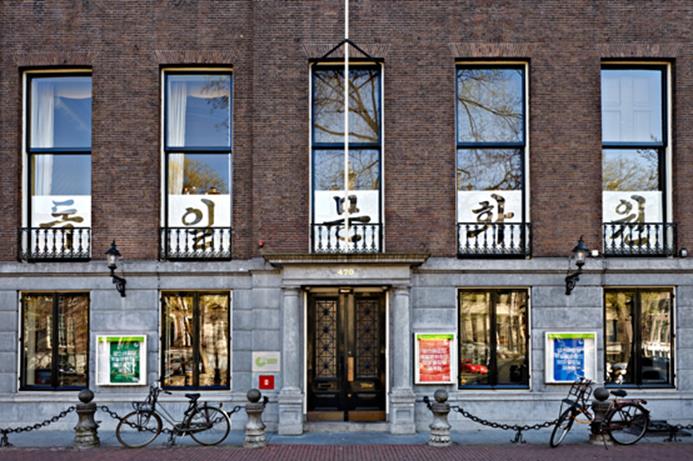
<암스테르담 독일문화원의 평양 – 열람실 재개원>, 2013 독일문화원 암스테르담 레터링
컨셉: 사라 반 더 하이데(Sara van der Heide)
레터링 페인팅: 강문식
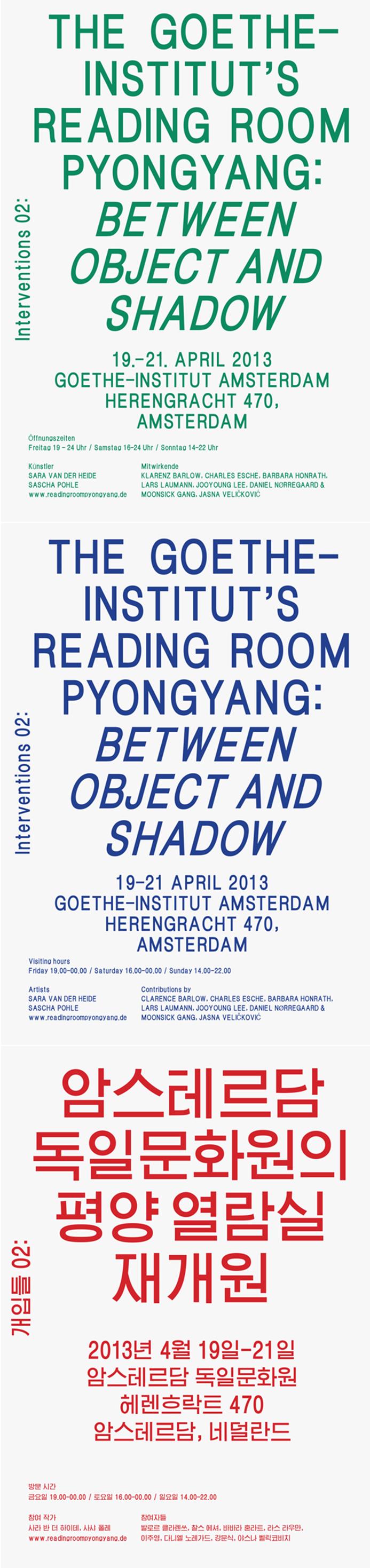
<암스테르담 독일문화원의 평양 – 열람실 재개원> 프린트 디자인, 2013
다니엘 노레가드(Daniel Nørregaard)와의 협업
오경민: 최근 디자인한 <공포영화 서바이벌 핸드북> 표지 디자인이 인상적이었어요. 한국의 디자이너들이 쉽게 쓸 생각을 하진 않을 것 같은 서체를 간결한 그래픽 어법과 조합하여 잘 풀어냈다고 생각해요. 사용한 글자 모양이 레오의 컬리 레터(curly letter)와 약간 비슷하다는 느낌을 받았는데, 레터링에 관한 관심이 연결됐다고 볼 수 있나요?
강문식: 그렇게 보일 수도 있겠지만, 접근은 약간 달랐어요. 기존에 많이 사용되는 서체들과는 차별화되는 서체를 찾고 싶었어요. 새로우면서도 책의 주제와 연결되는 모양새를 가진 서체들을 조사하다가 이 서체(물감체, 태시스템)를 발견하게 되었죠.
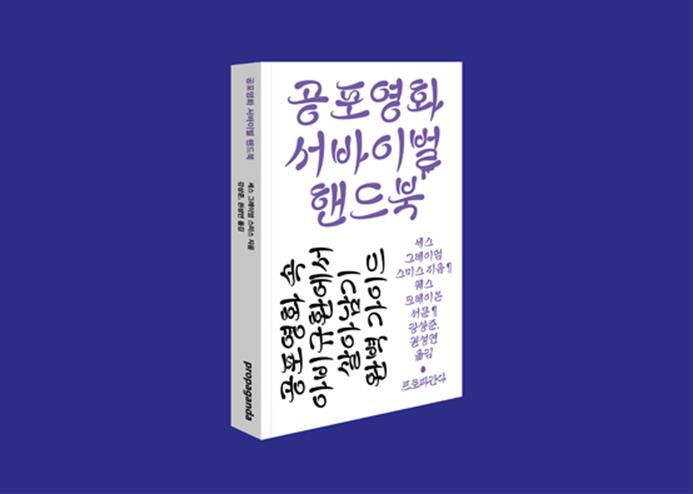
<공포영화 서바이벌 핸드북>, 프로파간다 출판, 2013
오경민: 작년 <브르노 비엔날레(Brno Biennial >에서 전시됐던 벨리고딕(Belly Gothic)도, 벨고딕(Bell Gothic)에 강문식씨 나름의 손맛을 가미한 것으로 보이던데요.
강문식: <공포영화 서바이벌 핸드북>은 서체 형태가 주는 느낌이 디자인의 중요한 부분이었다면, 벨리고딕은 시스템적인 문제를 건드린 것이었어요. 벨고딕이 가지고 있는 기술적 장점이자 특징인 잉크트랩이 인쇄기술의 발달로 그 의미가 퇴색되고 현재에는 스타일로만 남게 된 상황을 과장해서 표현한 서체였죠.
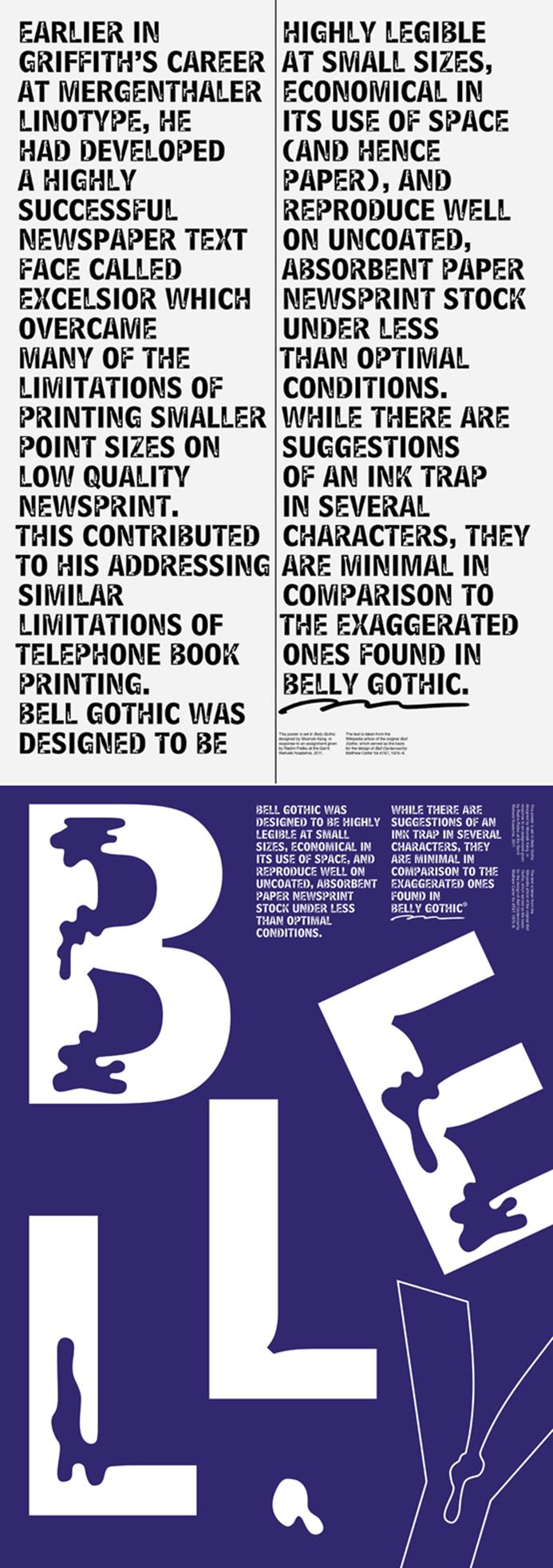
<Belly Gothic>, 2012
오경민: 각 프로젝트가 접근은 달랐지만, 비규범적, 비정형적 형태로 우연처럼 연결됐네요. 이번엔 학교 얘기를 해볼까요? 리트벨트 아카데미(Gerrit Rietveld Academie)에서의 생활은 어땠나요?
강문식: 한국 대학교와의 시스템적 차이가 가장 크게 다가왔어요. 교수, 조교, 학생 사이의 위계가 명확하게 구분된 조직이 아니라 각자의 역할을 따라 필요할 때 연결됐다가 해체되는 평등하고 자유로운 점 조직 같았어요. 그리고 모든 프로그램은 학생들이 공부하고 싶어하는 부분을 지원해 주기 위한 방향으로 디자인되어 있다는 느낌이었죠. 교육 내용에서도 지식 전달 위주가 아니라 주로 개념에 대해 접근했고, 필요한 지식은 학생들이 자율적으로 채워 넣어야 했어요. 지금은 당연한 것들이 돼버렸지만, 처음 학교생활을 시작할 당시에는 굉장히 새롭게 느껴졌어요.
오경민: 2011년 프라하에서 진행된 리트벨트 학생 전시회 <Rietveld at Prague>를 위해 디자인한 포스터에서, 리트벨트 아카데미와 리트벨트가 디자인한 의자를 단도직입적으로 연결한 부분뿐 아니라, 저명한 디자이너의 고급 의자를 대중적으로 친숙한 광고 전단 형식과 결합한 부분이 재미있었는데요, 문득 2년 전 강문식씨와 한 대화를 떠오르게 하더군요. “디자이너 친구와 익명으로 ‘찌라시’ 디자인 회사를 만들기로 했다”고 농담처럼 말했었죠. 이 포스터는 그 야심을 실현해 본 건가요?
<Rietvelt at Prague>, 2011
안근표와의 협업
강문식: 하하, 그렇게 볼 수도 있겠네요. 이 포스터는 리트벨트에서 같이 공부했던 안근표 형과의 공동 작업이었는데, 아이디어는 다큐멘터리 영화 <체코 드림(Czech Dream)>에서 얻었어요. 가짜 홍보 광고지를 이용해서 사람들을 전시로 유도하는 것이었죠.
오경민: 네덜란드의 가구 디자인과 체코의 다큐멘터리 영화를 리트벨트 아카데미와의 연결 고리로 삼은 것이군요. 문식씨의 디자인 작업 중 제가 유독 관심이 가는 작업들 사이에 공통점을 발견하는데요, 고급과 저급, 오래된 것과 새로운 것, 기성의 것과 그에 대한 반격, 기계적인 것과 손맛의 ‘중간 지점’을 볼 수 있다고나 할까요?
강문식: 그렇게 보셨다니 감사합니다. 작업 과정에서 제가 가장 중요하게 여기는 것이 조화로움이거든요. 한쪽으로 치우친 것보다는, 줄타기하는 느낌으로 불안한 듯 양쪽 다 놓치지 않는 균형감이요.
오경민: 마지막으로 현재 작업하고 있는 프로젝트를 설명해 주실 수 있나요?
강문식: <타이포잔치 2013> 프로그램 중 <무중력 글쓰기>에서 보여줄 작업을 진행 중이에요. 7명의 젊은 그래픽 디자이너와 7명의 젊은 시인이 1대1로 팀을 이루어, 시인은 시를 쓰고 디자이너는 움직이는 타이포그래피를 만드는 프로젝트에요. 서울 스퀘어 미디어 파사드에서 상영될 예정이고요. 고정된 지면 안에서만 작업하던 시인과 그래픽 디자이너가, 움직이는 영상에 어떻게 대응할 것인지 생각해 보는 재미있는 실험이 될 것 같아요.
저는 서효인 시인과 짝을 이뤘어요. 초반 작업 당시 서효인 시인이 제가 사하라 사막 여행에서 막 돌아왔다는 얘기를 듣고는, 여행의 감회를 세 가지 단어, 즉 동사, 형용사, 명사 각 한 단어로 표현해 달라고 요청했어요. 그리고 그 단어들을 모티브로 해서 <서울 사막>이라는 시가 만들어졌죠. 사람들이 거리를 걷다가 갑작스럽게 맞닥뜨리게 될 시를 만들고 또 보여주는 작업이기 때문에, 그 환경에 적합한 짧은 호흡으로 구성되었어요. 이 작업은 9월 24일에 상영됩니다.
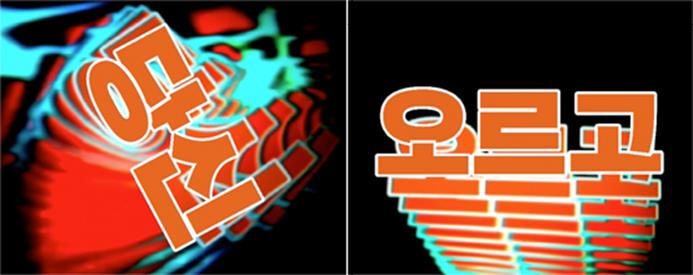
<서울 사막>, 2013
단채널 비디오, <타이포잔치 2013> ‘무중력 글쓰기’ 프로그램을 위해 서울스퀘어 미디어 캔버스 상영용으로 제작 /영상보기
인터뷰를 마친 후 그는, 3년여의 암스테르담 생활을 정리하고 새로운 도시에서의 삶을 시작하기 위한 막바지 차비를 하러 떠났다.
<How to make your life hard in one day>, 2011